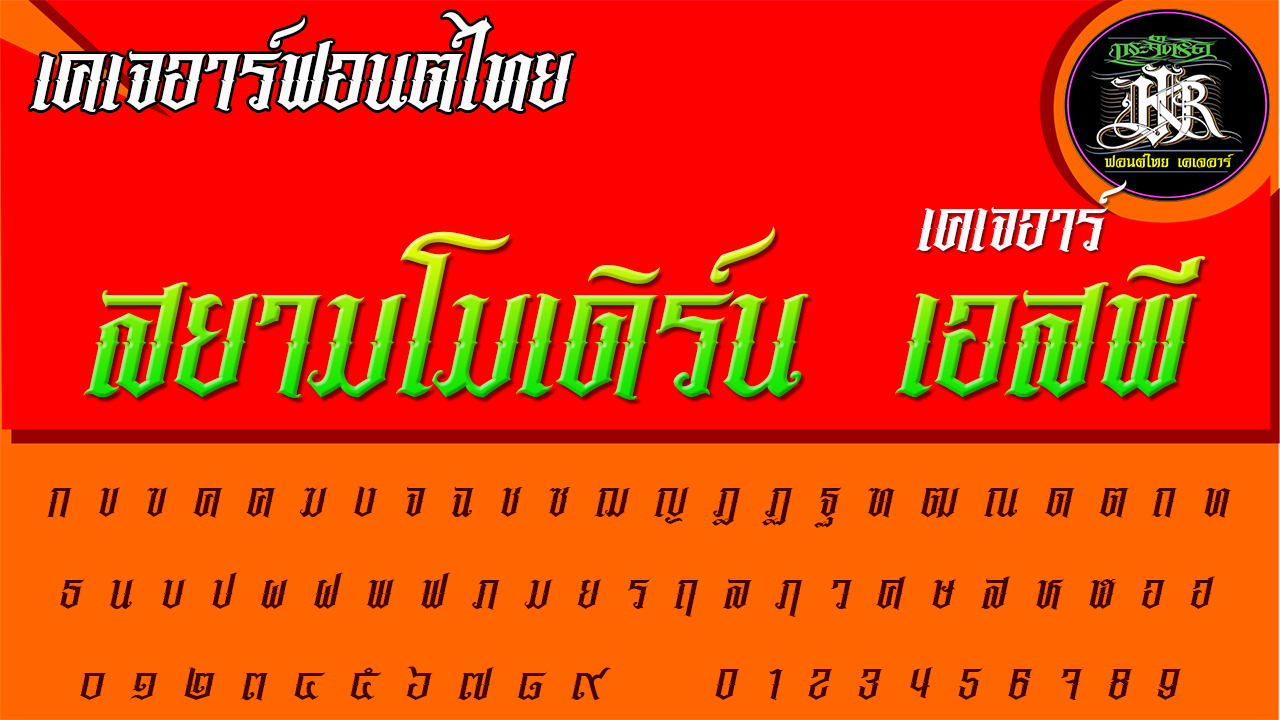
สยามโมเดิร์น (KJR SIAMMODERN)
ฟอนต์ไทยโมเดิร์น ทันสมัยได้มาตรฐาน ฟอนต์ชุดนี้มีทั้งหมด 4แบบด้วยกัน เหมาะกับงานออกแบบทั่วๆไป(ขอขอบคุณแทมเพลตจากนายพล ที่ให้ความสะดวกสบายในการทำงาน)